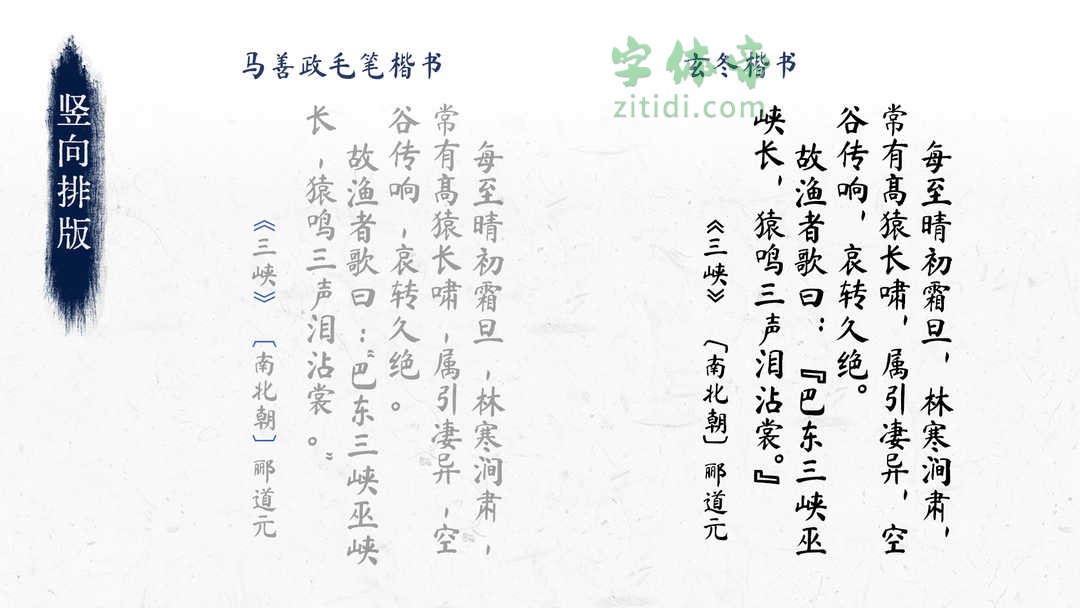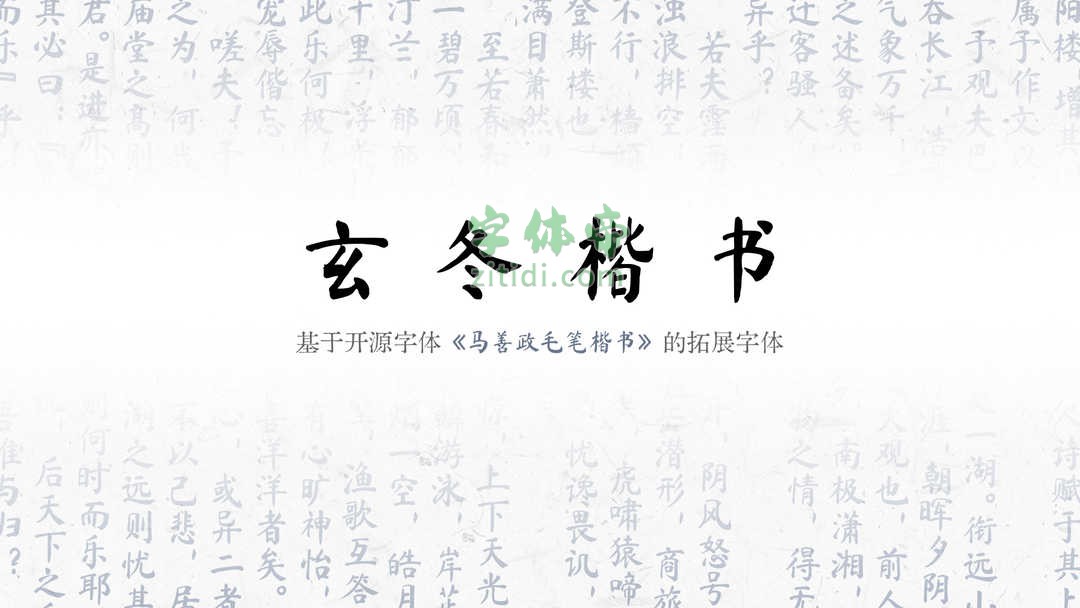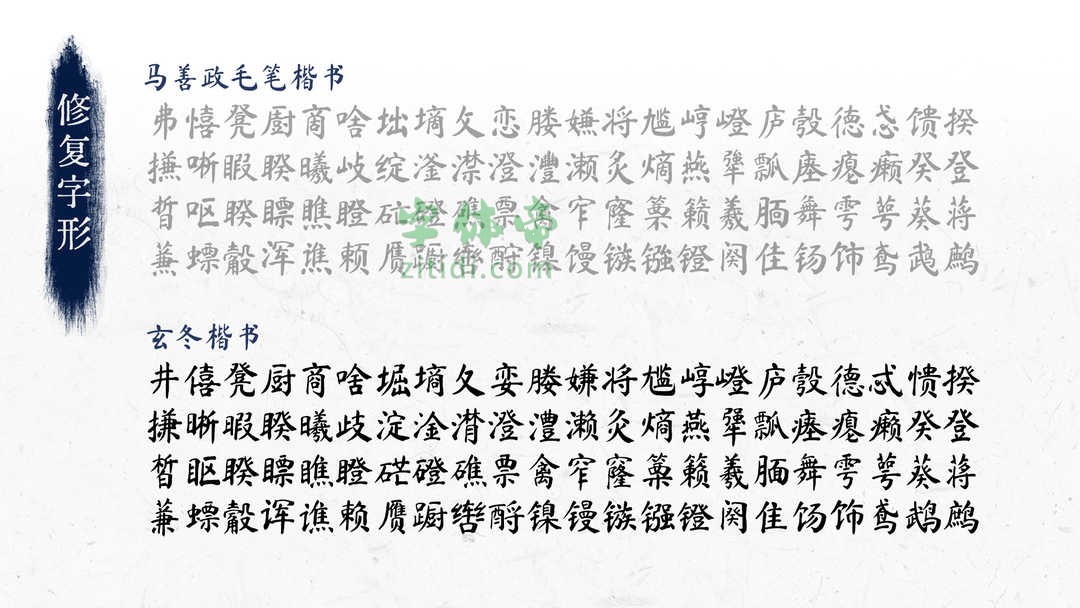
玄冬楷书为基于开源字体《马善政毛笔楷书》的拓展字体。在原版的基础之上修复了错误的字形并添加竖排排版的特性。
修改内容
- 修复以下88字:
井僖凳厨商啥堀墒夂娈媵嫌将尴崞嶝庐彀德忒愦揆
搛晰暇睽曦歧淀淦潸澄澧濑灸熵燕犟瓢瘗瘪癞癸登
皙眍睽瞟瞧瞪硭磴礁票禽窄窿篥籁羲腼舞雩萼葵蒋
蒹螵觳诨谯赖赝蹰辔酹镍镘镞镪镫阕隹饧饰鸢鹉鹧 - 调整都分汉字字面的问题。
- 增加
vert特性,用于竖向排版。 - 新增“啰瞭”二字,补全一级通用规范字。